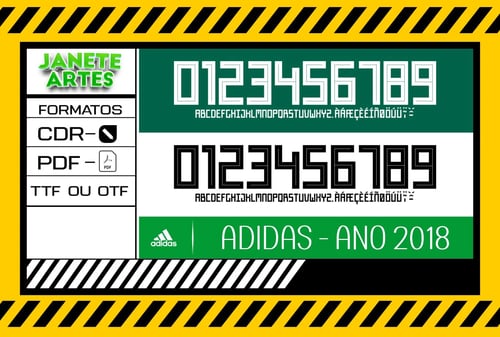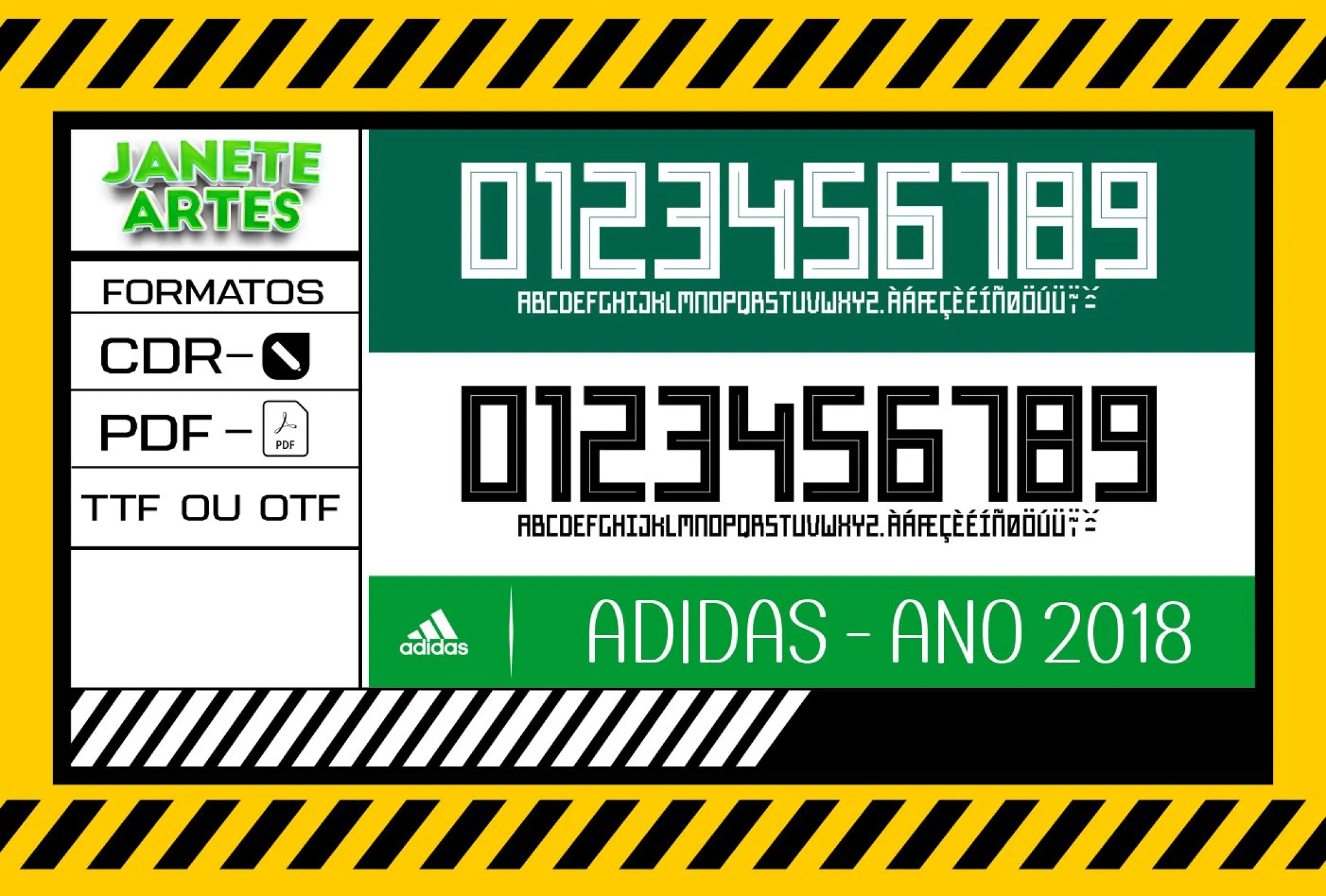
Camiseta unissex branca com logo no peito e estampa grande nas costas em fonte de time tipografia Adidas 2018, estilo moderno e esportivo, perfeita para fãs de futebol e moda urbana.
Fonte de Time Tipografia Adidas 2018
A origem da Fonte de Time Tipografia Adidas 2018
Imagine estar em um estádio lotado, a torcida vibrando, e sua camiseta personalizada com a fonte que fez história na temporada Adidas 2018. Essa fonte traz a emoção do futebol para o seu dia a dia, unindo paixão e estilo em uma peça única. Desde o lançamento das coleções esportivas Adidas, fãs e times se encantaram pela elegância dessa tipografia. Com ela, você pode dar vida às suas camisetas, mostrando sua identidade e apego às melhores temporadas do futebol.